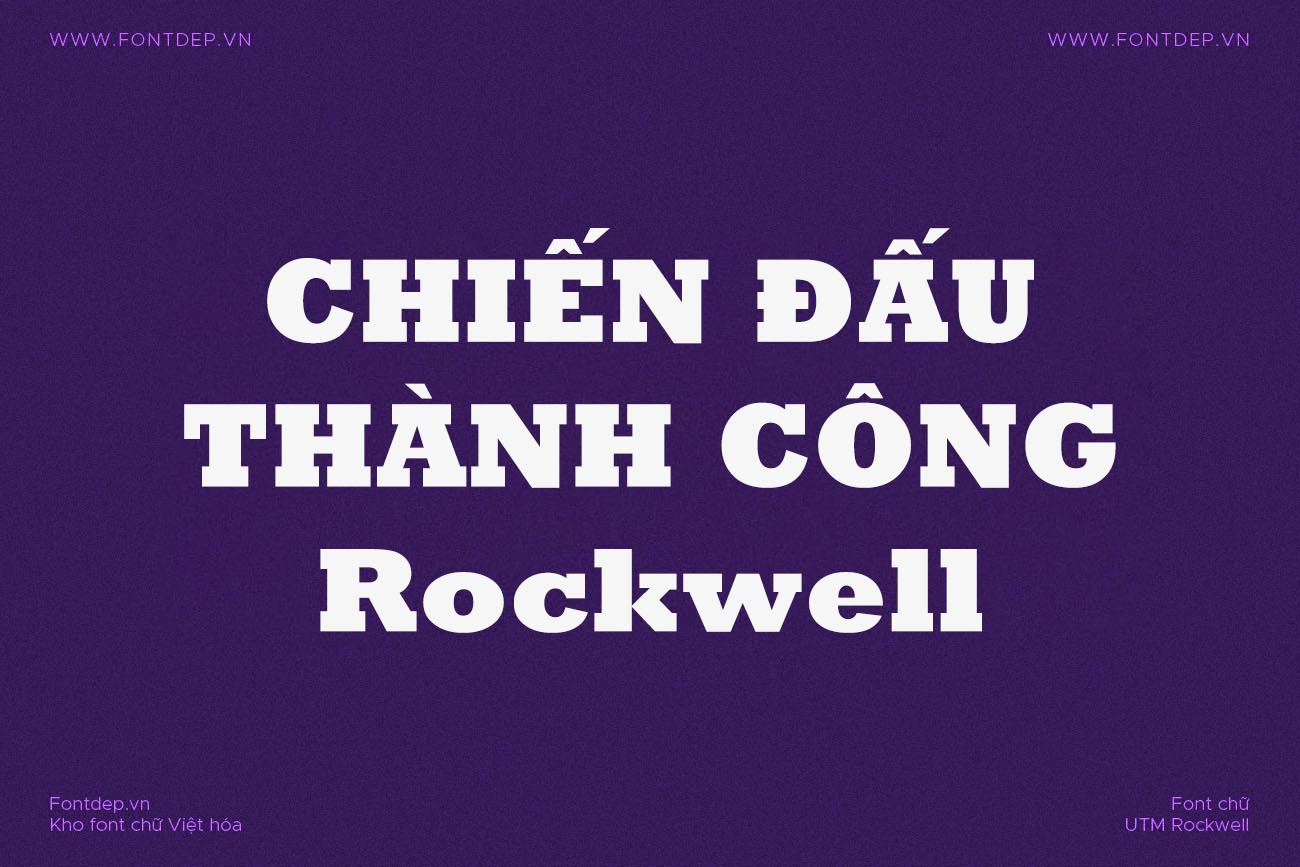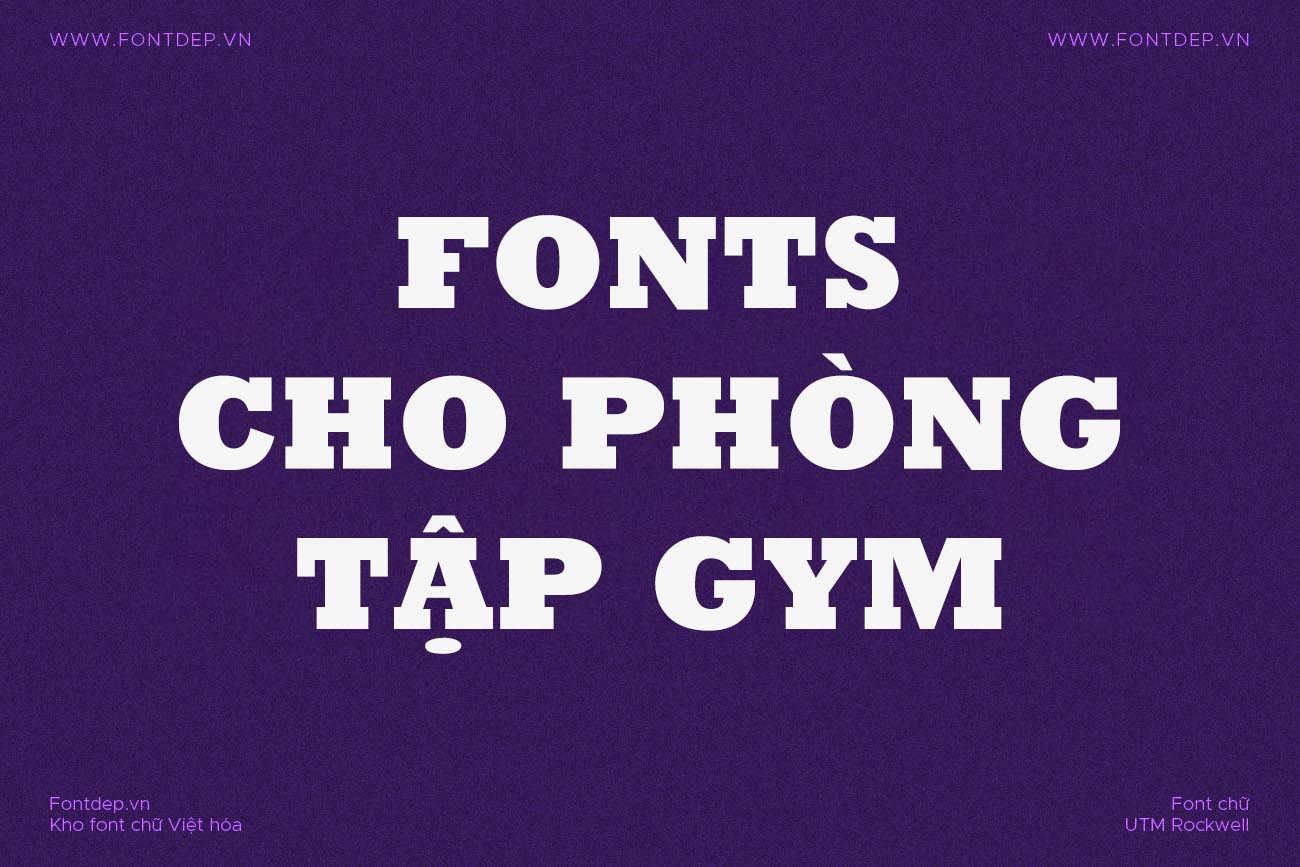
Phông Chữ Miễn Phí - UTM Rockwell Việt Hóa Mạnh Mẽ Cho Thể Thao
Tác giả Monotype
Việt hóa Team UTM
Trong lĩnh vực thiết kế đồ họa, đặc biệt là các ấn phẩm thể thao và gym, việc lựa chọn font chữ phù hợp đóng vai trò quan trọng trong việc truyền tải thông điệp. Một trong những lựa chọn nổi bật và được nhiều designer tin dùng chính là UTM Rockwell Việt Hóa.
Nguồn gốc và đặc điểm nổi bật
Font Rockwell ban đầu được phát triển bởi Monotype Design Studio và ra mắt năm 1934, thuộc nhóm Slab Serif với các đường nét vuông vắn, mạnh mẽ. Phiên bản UTM Rockwell Việt Hóa được nhóm UTM chuyển đổi sang chuẩn Unicode, hỗ trợ đầy đủ dấu tiếng Việt, giúp người dùng dễ dàng ứng dụng trong thiết kế nội địa.
Điểm nổi bật của font chữ này nằm ở chữ in đậm, chân vuông chắc khỏe, tỷ lệ cân đối và dễ đọc. Chính những yếu tố đó mang lại cảm giác sức mạnh, sự bền bỉ và quyết tâm, vô cùng phù hợp cho các thiết kế trong lĩnh vực thể thao, fitness, poster cổ động hay banner phòng gym.
Ứng dụng trong thiết kế
Với phong cách cứng cáp và hiện đại, UTM Rockwell Việt Hóa thường được sử dụng trong:
• Logo và thương hiệu thể thao: tạo sự mạnh mẽ và chuyên nghiệp.
• Poster, banner phòng gym: gây ấn tượng mạnh ngay từ cái nhìn đầu tiên.
• Ấn phẩm cổ động: thể hiện khí thế và tinh thần chiến đấu.
• Thiết kế áo đấu, dụng cụ thể thao: tăng tính nhận diện và phong cách.
Tại sao nên chọn UTM Rockwell Việt Hóa?
Không chỉ mang lại sự mạnh mẽ trong từng chi tiết, UTM Rockwell còn là font chữ dễ sử dụng, hỗ trợ đa dạng nền tảng, đảm bảo hiển thị tốt trong cả in ấn và digital. Đây là lý do nó trở thành lựa chọn hàng đầu cho designer trong lĩnh vực thể thao và fitness.
Nếu bạn đang tìm kiếm một font chữ thể thao mạnh mẽ, hiện đại và dễ ứng dụng, thì UTM Rockwell Việt Hóa chính là công cụ không thể thiếu trong bộ sưu tập thiết kế của bạn.